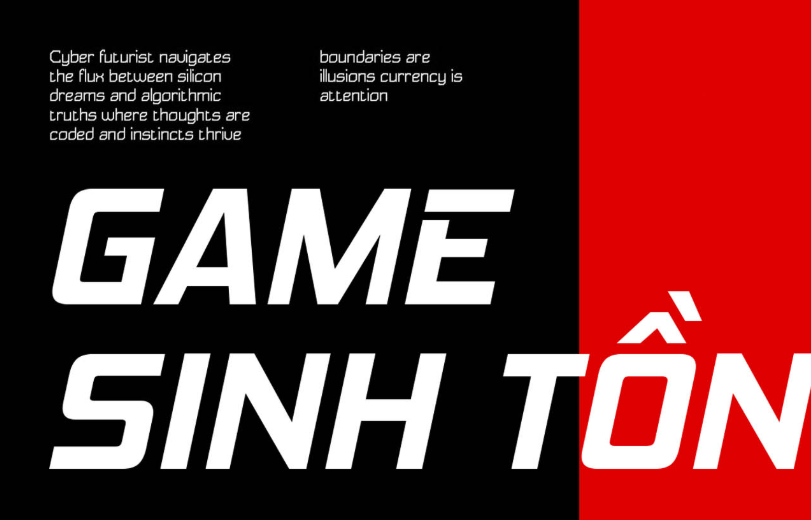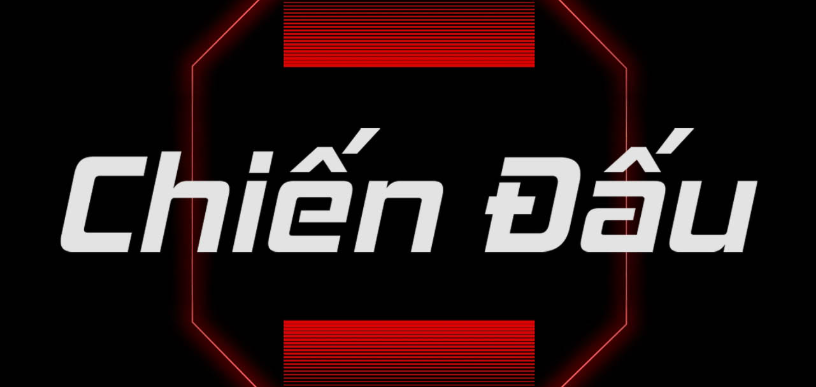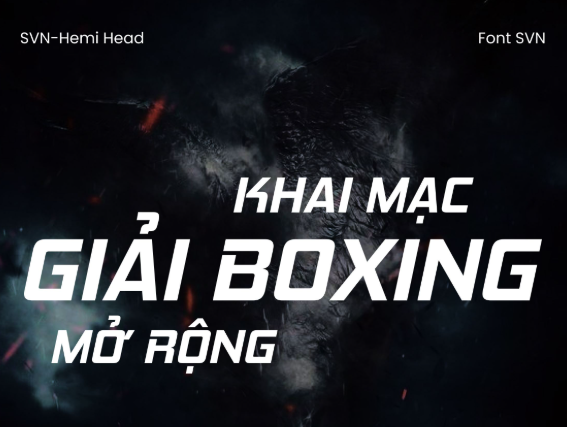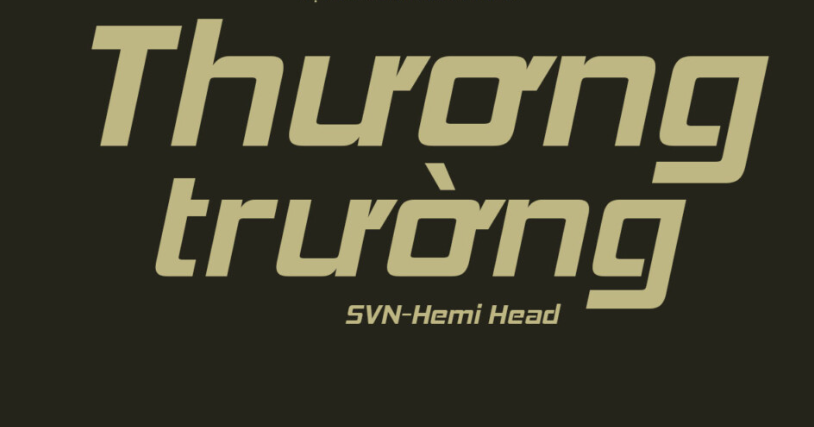
Font Hemi Head Việt hóa (hay còn được biết đến với tên gọi phổ biến Font SVN Hemi Head Việt hóa) là bộ phông chữ không chân (Display Sans-serif) mang phong cách viễn tưởng (Sci-fi) và cơ khí cực kỳ mạnh mẽ, được sáng tạo bởi nhà thiết kế Ray Larabie (Typodermic Fonts). Lấy cảm hứng từ các khối động cơ xe cơ bắp (HEMI engine) và công nghệ tương lai, phông chữ này nổi bật với các đường cắt vát sắc sảo, cấu trúc hình khối góc cạnh và sức nặng thị giác uy quyền. Doozypack.vn cung cấp link tải trọn bộ phông chữ chuẩn kỹ thuật, giúp bạn sở hữu phông chữ đậm chất techno này, hỗ trợ đầy đủ tiếng Việt không lỗi dấu để tự tin thiết kế bao bì và bộ nhận diện thương hiệu.
Đặc điểm thẩm mỹ độc đáo của bộ font Hemi Head
Hemi Head không đi theo sự tròn trịa hay tối giản trung tính; nó mang đến một ngôn ngữ thị giác đầy tính bùng nổ, tái hiện trọn vẹn tốc độ, sức mạnh cơ khí và công nghệ tương lai.
Phong cách Sci-fi Techno sắc sảo lấy cảm hứng từ cơ khí
Đặc trưng lớn nhất của Font Hemi Head Việt hóa là các góc vát chéo dứt khoát tại các điểm đầu và đuôi ký tự, mô phỏng những đường cắt trên các khối động cơ hiệu suất cao. Cấu trúc chữ sở hữu độ dày nét (weight) cực lớn, tạo nên một mảng khối văn bản vững chãi, uy lực và rất thu hút thị giác. Khi đặt Hemi Head làm tiêu đề trên bao bì, sản phẩm của bạn sẽ ngay lập tức khẳng định được phong cách thể thao, hiện đại và cực kỳ nam tính.
Cấu trúc hình khối góc cạnh mang lại uy lực mạnh mẽ
Các ký tự của SVN Hemi Head sở hữu tỷ lệ cân đối, các đường giao nét vuông vức mang lại cảm giác kỷ luật, chính xác và minh bạch tuyệt đối. Sự kết hợp này giúp tiêu đề bản thiết kế giữ được sự đĩnh đạc, cá tính và không hề gây cảm giác nặng nề, rất phù hợp với các mẫu hộp giấy định vị ở phân khúc kỹ thuật và gaming.
Ưu điểm nổi bật của bản Font Hemi Head Việt hóa
Khi ứng dụng các phông chữ cơ khí quốc tế vào thị trường trong nước, sự chỉn chu về dấu câu là yếu tố quyết định đến tính chuyên nghiệp của ấn phẩm:
- Khắc phục triệt để lỗi dấu tiếng Việt: Phiên bản Việt hóa đã được đội ngũ thiết kế trau chuốt thủ công từng dấu câu. Các dấu sắc, huyền, hỏi, ngã, nặng được vẽ với góc vát và độ dày đồng điệu cùng thân chữ gốc, không gây cảm giác chắp vá hay làm biến dạng cấu trúc hình học.
- Kiểm soát hiện tượng tràn mực (Dot Gain) tại khe chữ nhỏ: Các khoảng hở bên trong chữ cái của Hemi Head (như chữ ‘e’, ‘a’) khá hẹp. Khi in trên giấy có độ thấm mực cao như giấy Kraft, mực có thể bị lan làm bít kín các lỗ hở này. Bạn nên giữ size chữ tiêu đề tối thiểu từ 10pt trở lên để bảo đảm độ sắc nét.